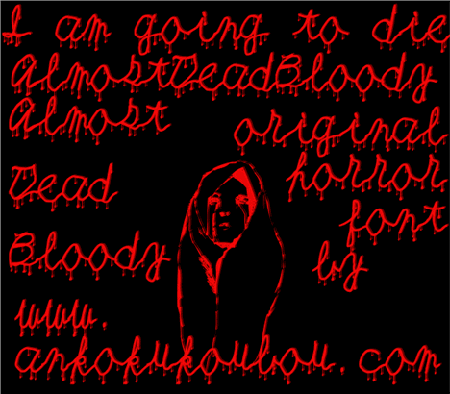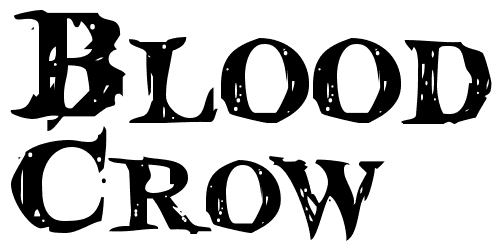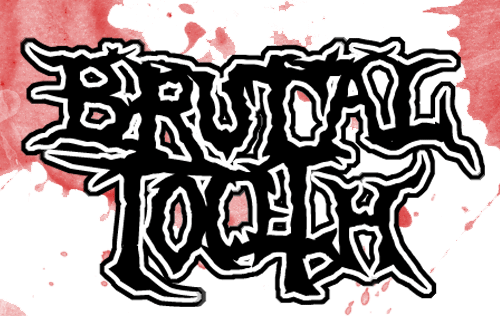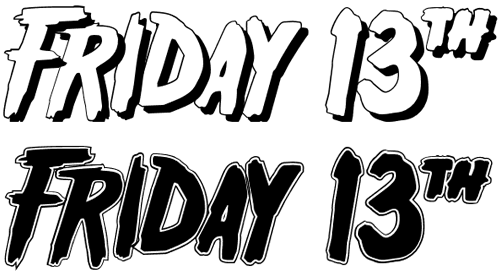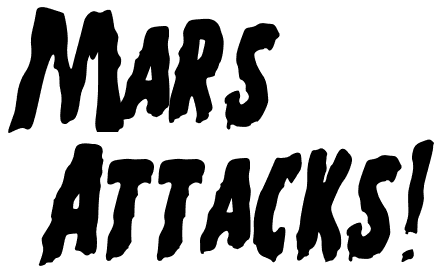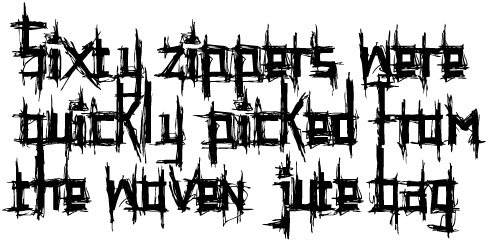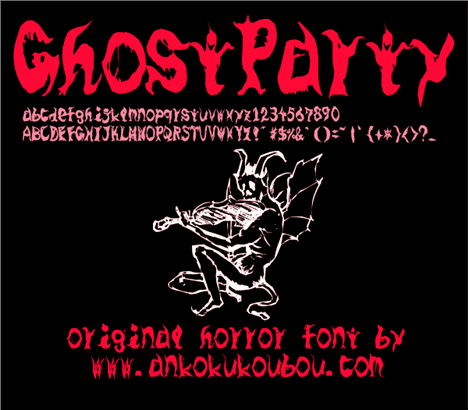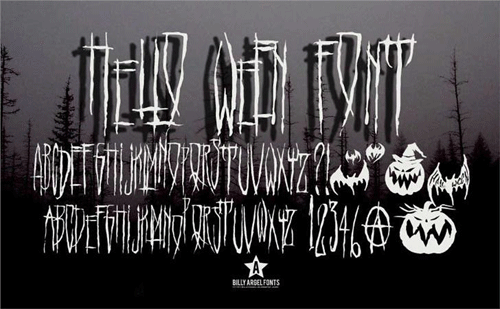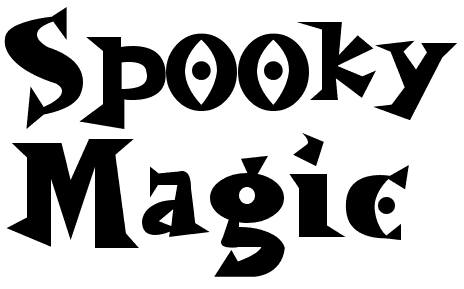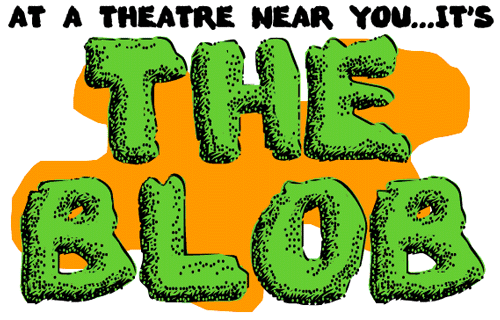
50 бесплатных готических шрифтов
готические-шрифты Типографика неотъемлемая часть любого дизайна, будь то печатное издание или интернет проект. Иногда, достаточно только шрифтов, для того чтобы выразить свою мысль зрителю. За частую мы используем не так много шрифтов, ведь покупать их для создания всего-лишь одного проекта не так уж и целесообразно.
В этой подборке собраны более 50 абсолютно бесплатных шрифтов. Если у вас наклевывается проект, который вы бы хотели создать в готическом стиле, эта подборка то что вам нужно. Грязные шрифты, шрифты с потеками, шрифты для Хэллоуина, страшные и жуткие шрифты, тут вы найдете огромное разнообразие таких ресурсов.
Шрифт Cold Night for Alligators
Шрифт
Жирный шрифт Feast of Flesh BB
Жирный шрифт
Тонкий неравномерный шрифт Nightmare
Тонкий неравномерный шрифт
Обведенный шрифт Brutal Tooth
Обведенный шрифт
Рваный шрифт Creepsville
Рваный шрифт
Жирный обведенный шрифт Friday 13
Жирный обведенный шрифт
Шрифт с потертостями Survival Horror
Шрифт с потертостями
Готический шрифт Blood Crow
Готический шрифт
Шрифт кистью Mars Attacks
Шрифт кистью
Тонкий готический шрифт Horror
Тонкий готический шрифт
Шрифт с элементами иллюстрации Holitter Spike
Шрифт с элементами иллюстрации
Шрифт с брызгами краски DBE-Beryllium
Шрифт с брызгами краски
Грязный прописной шрифт The haine au carre
Грязный прописной шрифт
Затертый грязный шрифт Cannibal Corpse
Затертый грязный шрифт
Иллюстрированный шрифт Solstice Of Suffering
Иллюстрированный шрифт
Шрифт с черепами Zombified
Шрифт с черепами
Шрифт в стиле Хэллоуина Kreepshow Frigid
Шрифт в стиле Хэллоуина
Неаккуратный шрифт с потеками HoMicIDE EFfeCt
Неаккуратный шрифт с потеками
Кровавый шрифт Bloodsuckers
Кровавый шрифт
Угловатый шрифт с потеками Brain Damage
Угловатый шрифт с потеками
Иллюстрированный шрифты в точечку The Blob
Иллюстрированный шрифты в точечку
Жирный шрифт с потеками краски Plasma Drip Font
Жирный шрифт с потеками краски
Шрифт с пробелами Were Wolf Font
Шрифт с пробелами
Гранж шрифт You Murderer Font
Гранж шрифт
Необычный шрифт Creepygirl
Необычный шрифт
Симпатичный шрифт Spookymagic
Симпатичный шрифт
Хэллоуин шрифт Hello ween font
Хэллоуин шрифт
Битый шрифт Black Oak
Битый шрифт
Аккуратный готический шрифт Resident Evil
Аккуратный готический шрифт
Шрифт с элементами веток деревьев Wild Wood
Шрифт с элементами веток деревьев
Неровный шрифт Sin of the innoccent
Неровный шрифт
Стилизованный шрифт Windswept MF
Стилизованный шрифт
Устрашающий шрифт 13th Ghostwrite
Устрашающий шрифт
Потекший шрифт Splywaj
Потекший шрифт
Кровавый шрифт Almost Dead Bloody
Кровавый шрифт
Адский шрифт GhostParty
Адский шрифт
Шрифт с завитками Bosque Encantado
Шрифт с завитками
Шрифт в виде косточек 4 Dogs
Шрифт в виде косточек
Стильный шрифт BN Manson Nights
Стильный шрифт
Шрифт в готическом стиле Amhole
Шрифт в готическом стиле
Шрифт с узорами Vtks espinhuda
Шрифт с узорами
Прописной шрифт Gantz
Прописной шрифт
Шрифт от руки Last N Line
Шрифт от руки
Готический шрифт Carsi
Готический шрифт
Обведенный шрифт Dzr Mental
Обведенный шрифт
Шрифт в виде набросков Psychotic
Шрифт в виде набросков
Размазанный шрифт Convalescence
Размазанный шрифт
Шрифт с потертостями и потеками Cocaine Sans
Шрифт с потертостями и потеками
Почерканный шрифт Knife Fight
Почерканный шрифт
Грязный шрифт с пробелами Blasphemy
Грязный шрифт с пробелами
Жирный грязный шрифт El&font Block
это сатана а не готика %)
А русские символы поддерживают?
У меня ассоциация с готикой — это красивые готические соборы. Ождания были —
красивые вытянутые шрифты строгой стилистики.
А здесь копец какой-то, с духом мертвячины.
Ахереть то что надо, жаль русского нет